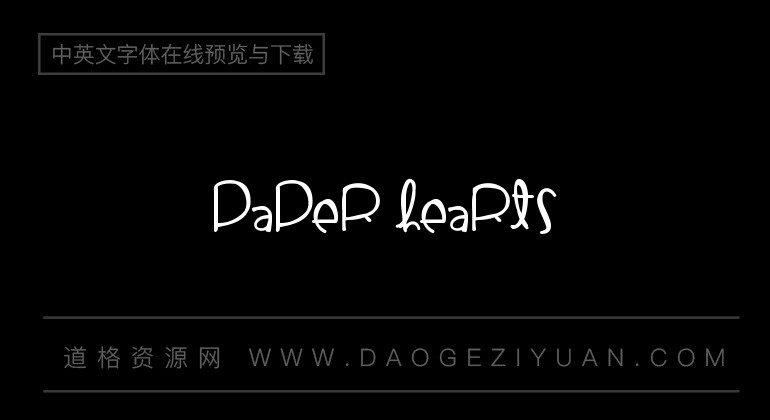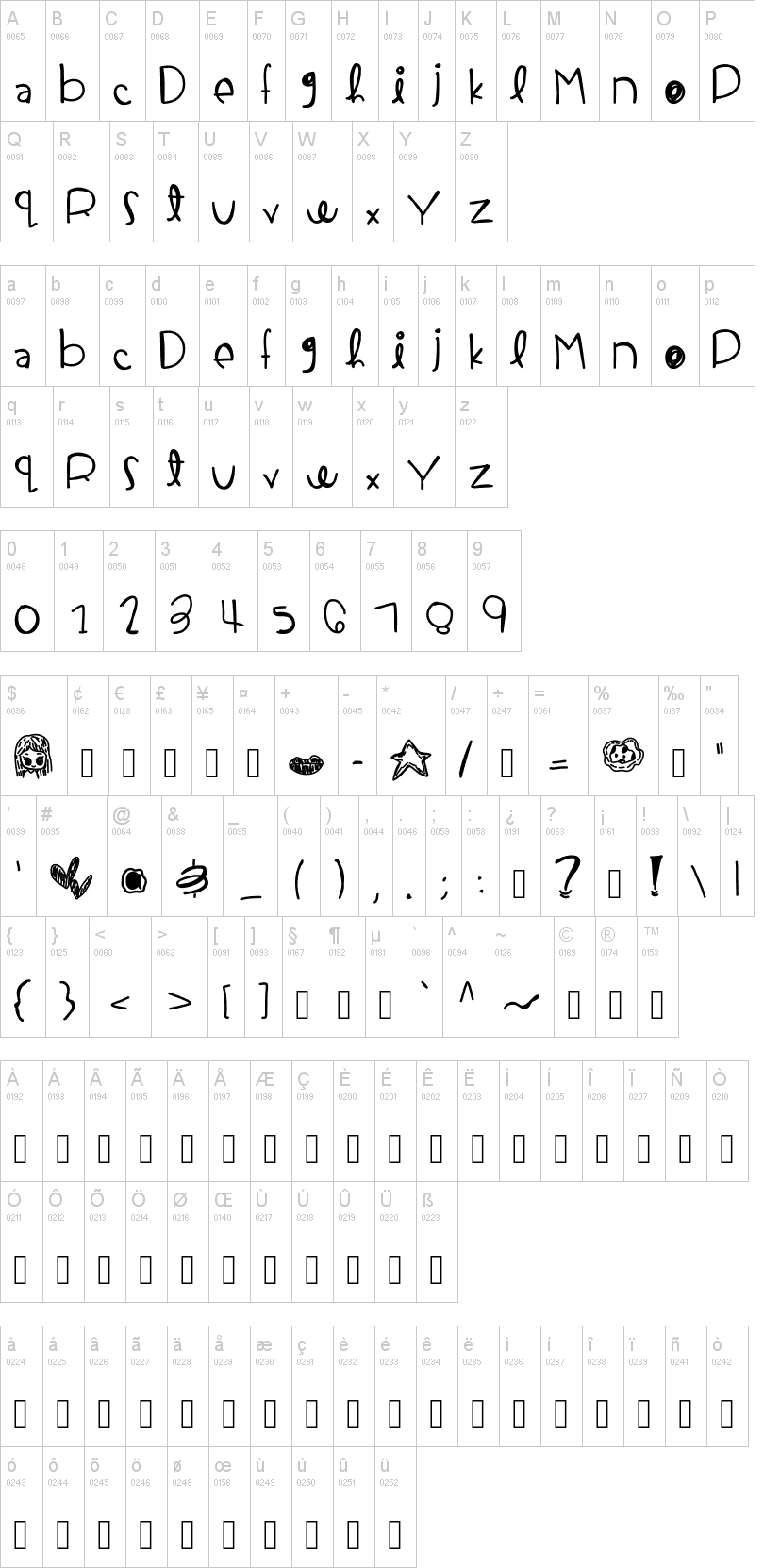
Paper Hearts 字体是一种手写字体,有一种可爱又轻快的感觉。字母看起来像是手写的,有点不规则但不失清晰度。字体中有一些字母会带有花边或心形装饰,这使它看起来更加浪漫和柔和。Paper Hearts 字体适合用于卡片、海报、手写风格的设计等情景,尤其是在需要传达温馨、爱情或亲密感的时候。内容介绍
Paper Hearts是一款非常不错的手写艺术字体,具有很好的视觉感,适合于文化类的宣传设计、商业类品牌的广告和产品包装设计以及个性化文字排版等较多场景。